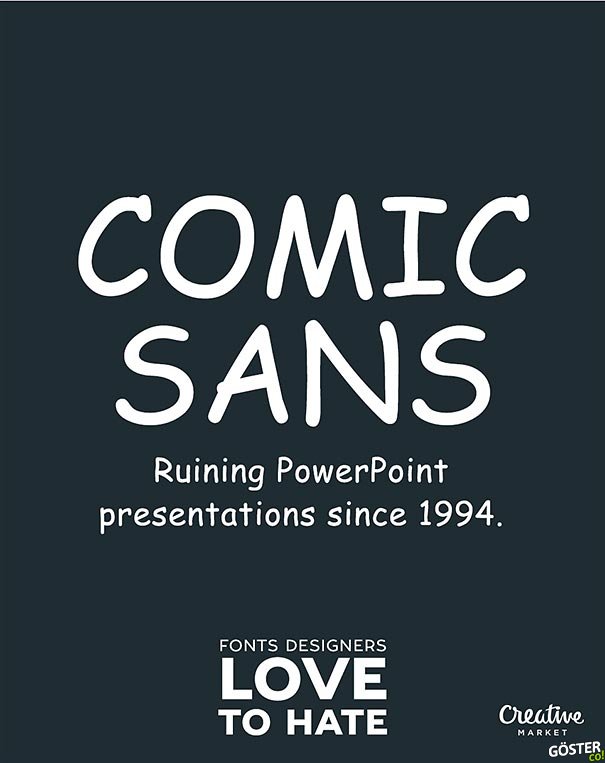
İnsanların Nefret Etmekten Keyif Aldığı 11 Yazı Tipi
Bazı fontlar vardır, evlat olsa sevilmez. Aslında o kadar da kötü değildirler, hatta bazısı...
Bazı fontlar vardır, evlat olsa sevilmez. Aslında o kadar da kötü değildirler, hatta bazısı kullanıldığı yerler ve çıkış amaçları göz önüne alındığında önemli de sayılırlar ama yine de yaranamazlar kimseye. İşte o fontlardan en bilindik 11 tanesi bu galeride. Çoğundan tasarımcılar ve siz internet gezginleri nefret ediyorsunuz.
Comic Sans: Nefret edilenlerin atası. 1994’ten beri PowerPoint sunumlarını berbat etmekte üstüne yok.